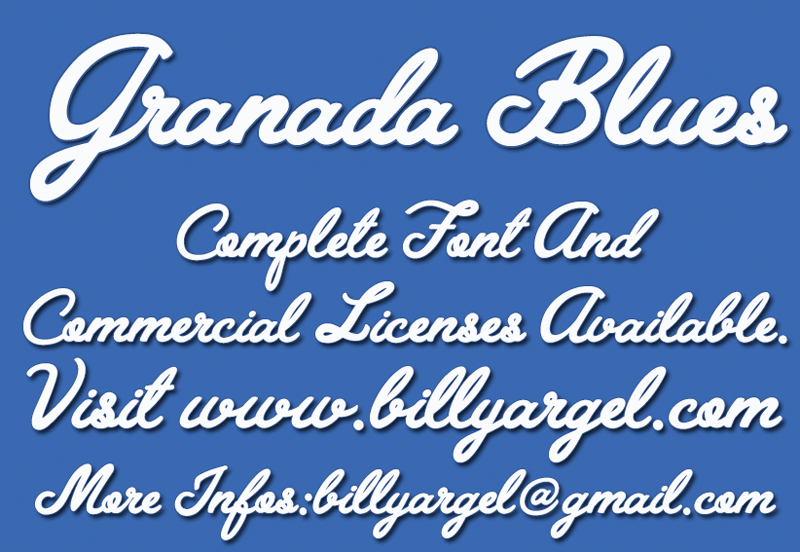
A Granada Blues Font é uma deliciosa adição para quem busca um estilo tipográfico fluido e versátil na sua próxima projeto de design. Esta elegante fonte é ideal para desfrutar e personalizar, graças a seu caráter artístico e expressivo. Desenvolvida pelo designer Billy Argel, esta linhagem única ganha vida em cada caractere, permitindo uma variedade impressionante de usos – seja para aplicações pessoais ou comerciais. Essa fonte não só é suave aos olhos por sua tipografia fluida e elegante, mas também oferece um toque único que se adequa perfeitamente a qualquer projeto em que você decida aplicá-la. Seja no design de letras, gráficos digitais ou até mesmo em arte digital, a Granada Blues Font tem o poder de transformar seus projetos em algo inesquecível. A fonte é gratuita para uso pessoal, mas se você desejar usá-la comercialmente ou precisar da fonte completa, Billy Argel está à disposição para atendê-lo. Não deixe de visitar sua página web e conhecer mais sobre as outras fontes criativas que ele oferece. Para obter informações mais detalhadas, entre em contato diretamente com Billy Argel através do email:  Visite o site oficial e acompanhe Billy Argel no Facebook para ficar por dentro de novidades e dicas sobre design.